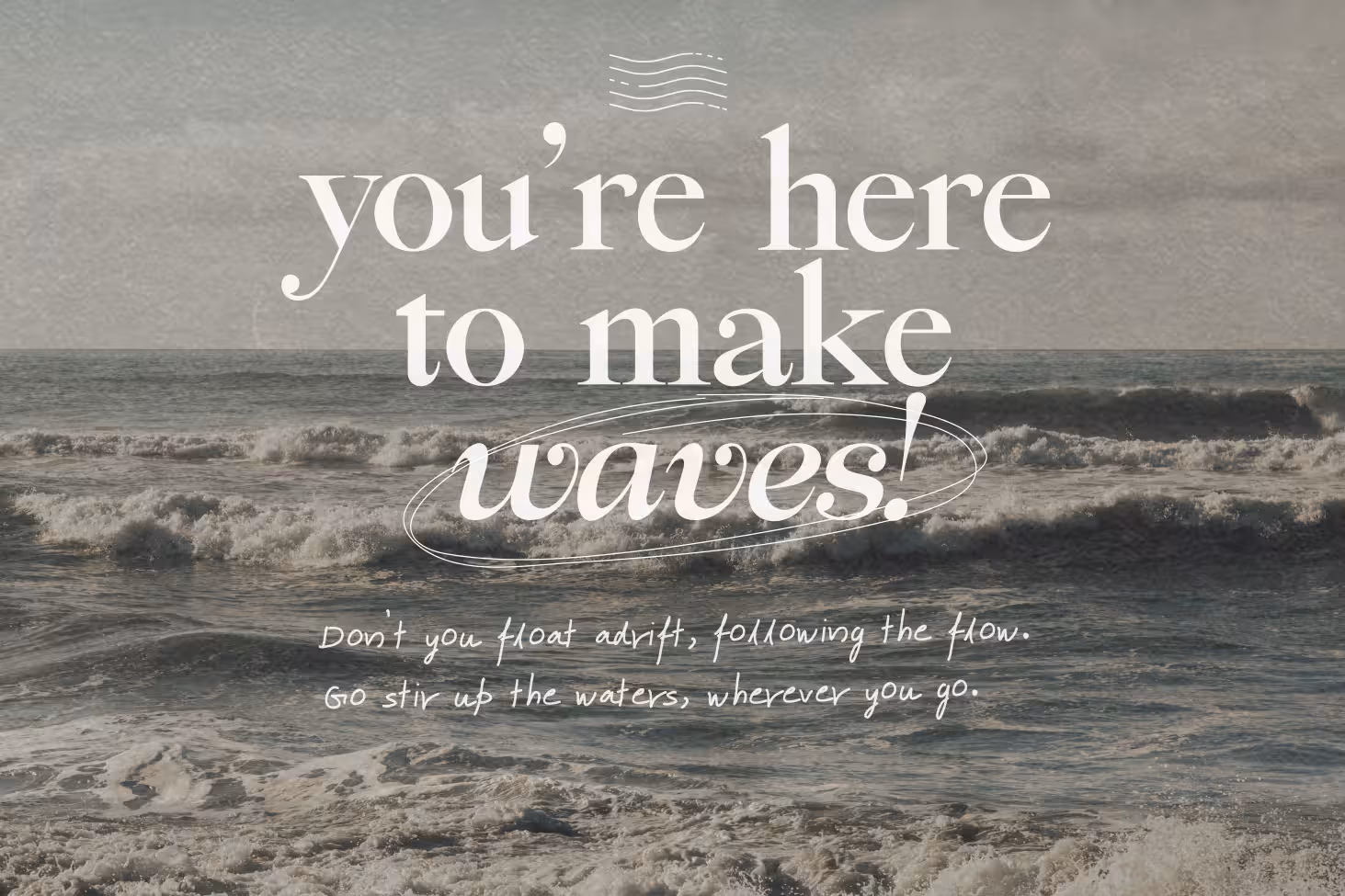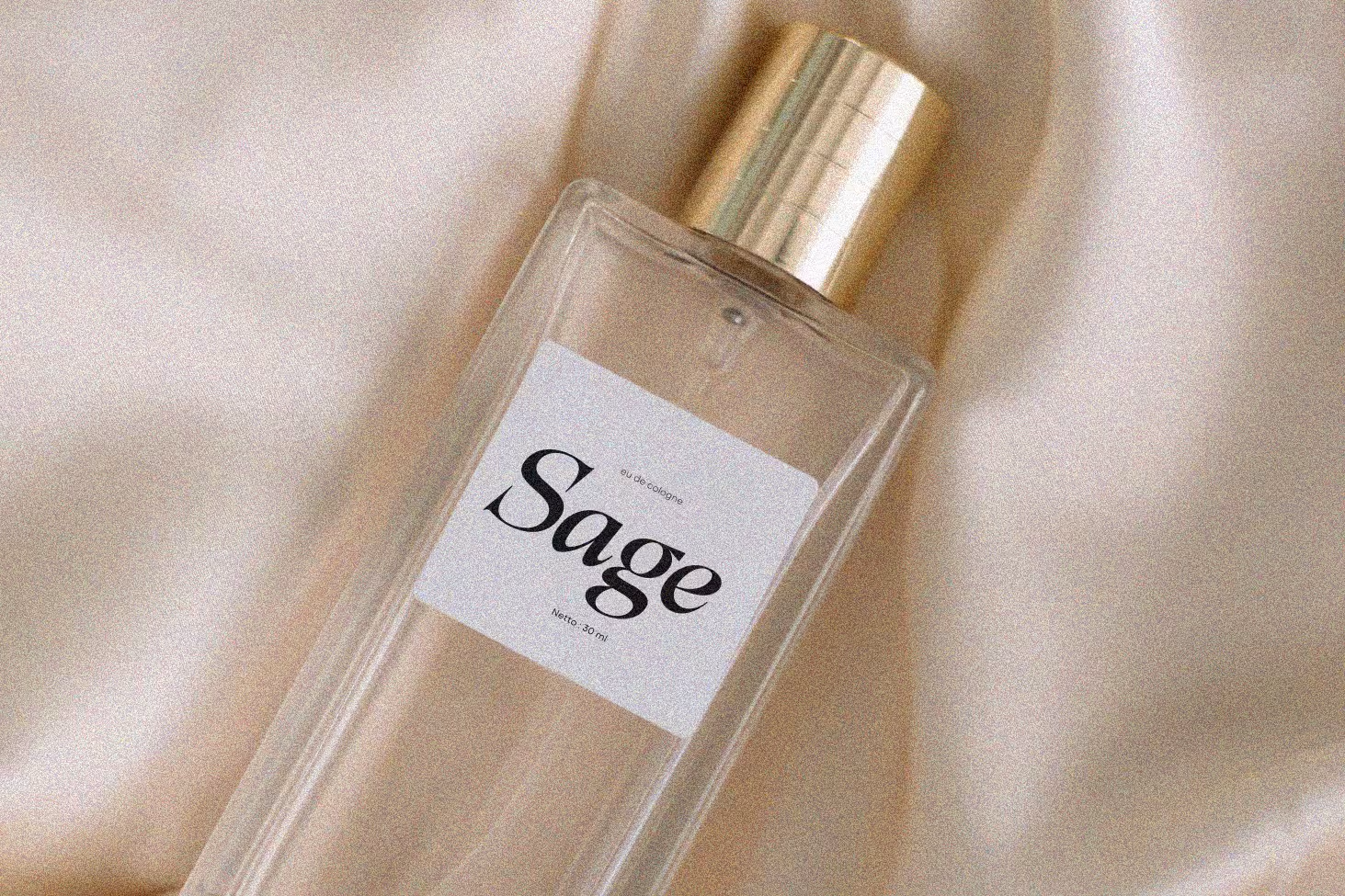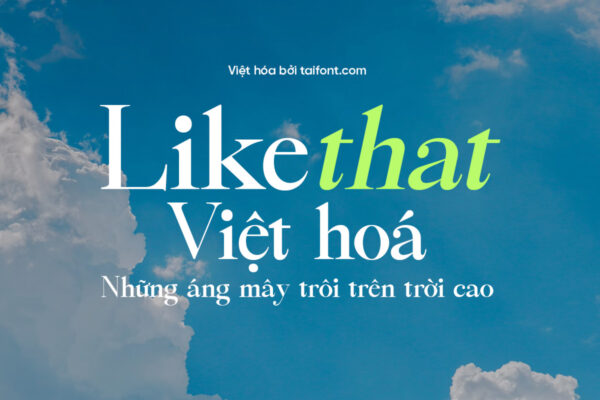
Giới thiệu về Font TF Likethat Regular & Italic Việt hóa
TF Likethat Việt hóa là một bộ font chữ có chân (serif) nổi bật với thiết kế đậm, chắc chắn và đầy ấn tượng. Với hai phiên bản Regular (thẳng) và Italic (nghiêng), bộ font này mang đến sự linh hoạt trong việc thể hiện thông điệp, toát lên phong thái uy quyền, sang trọng và chuyên nghiệp, lý tưởng cho mọi ấn phẩm cần sự rõ ràng và cuốn hút.
Với đặc điểm là nét có chân dày, chắc chắn, tính thẩm mỹ cao và khả năng ứng dụng đa dạng, Likethat là lựa chọn hoàn hảo cho các thiết kế muốn truyền tải sự mạnh mẽ, uy tín và sự độc đáo, đặc biệt là trong các lĩnh vực:
- Thiết kế tiêu đề: Hoàn hảo để tạo các tiêu đề chính (headline), slogan, hoặc thông điệp quảng cáo trên poster, banner, hoặc bất kỳ ấn phẩm nào cần sự chú ý tối đa. Nét chữ đậm và chắc chắn của font giúp thông điệp của bạn nổi bật, dễ đọc và truyền tải một cách hiệu quả ngay từ cái nhìn đầu tiên.
- In ấn: Lý tưởng cho các ấn phẩm in ấn đòi hỏi sự mạnh mẽ và rõ ràng như tạp chí, báo cáo, brochure, catalogue, hoặc danh thiếp. Độ sắc nét và chắc chắn của font giúp nội dung được truyền tải một cách hiệu quả, ngay cả trên nhiều chất liệu giấy khác nhau.
- Tạp chí và Thời trang: Phù hợp để sử dụng cho các tiêu đề chính, lời dẫn, hoặc nội dung bài viết trong các tạp chí về kinh doanh, thời trang, kiến trúc hoặc các ấn phẩm chuyên môn. Nét chữ đậm của font giúp tăng tính trang trọng và dễ đọc, đồng thời tạo cảm giác cao cấp, thu hút độc giả.
- Thiết kế nhận diện thương hiệu: Có thể dùng cho logo, tagline hoặc bộ nhận diện thương hiệu của các công ty, doanh nghiệp muốn truyền tải sự hiện đại, uy tín và sự đáng tin cậy.
Với TF Likethat Việt hóa, bạn có thể dễ dàng thổi hồn mạnh mẽ, uy tín và vẻ đẹp hiện đại vào các thiết kế, tạo ra những sản phẩm không chỉ đẹp mắt mà còn cực kỳ ấn tượng và có khả năng thu hút sự chú ý tối đa.